Font SHX là gì? Vì sao quan trọng với bản vẽ CAD Việt Nam?
Font SHX (Compiled Shape File) là định dạng font chuyên dụng của AutoCAD, xuất hiện từ những phiên bản CAD đầu tiên vào thập niên 1980. Khác với font TTF của Windows, SHX là font vector dạng nét đơn, được biên dịch từ file nguồn .SHP, nên có dung lượng nhẹ và tối ưu cho bản vẽ kỹ thuật.
Nhờ cấu trúc line/arc đơn giản, font SHX giúp AutoCAD zoom, pan và REGEN nhanh hơn, hạn chế tăng dung lượng file DWG. Khi in hoặc xuất PDF, chữ vẫn giữ dạng vector sắc nét. Độ dày nét không cố định trong font mà được kiểm soát qua layer, lineweight hoặc plot style (.CTB/.STB).
Một ưu điểm đáng chú ý của SHX là khả năng hỗ trợ Big Font cho các hệ chữ có lượng ký tự lớn và Unicode SHX (Unifont), vì vậy định dạng này vẫn được dùng phổ biến trong nhiều bản vẽ CAD tại Việt Nam.
Tiêu chí |
SHX |
TTF |
|
Cấu trúc |
Nét đơn (stroke) |
Outline đầy đặn |
|
Hiệu suất |
Nhanh, nhẹ |
Nặng hơn khi bản vẽ có nhiều text |
|
Độ dày chữ |
Kiểm soát qua layer, lineweight hoặc plot style |
Phụ thuộc vào thiết kế của font |
|
Vertical text |
Có hỗ trợ |
Hạn chế |
|
Big Font |
Có |
Không |
|
Phù hợp |
Bản vẽ kỹ thuật, hồ sơ CAD |
Bản vẽ chú trọng tính trình bày |
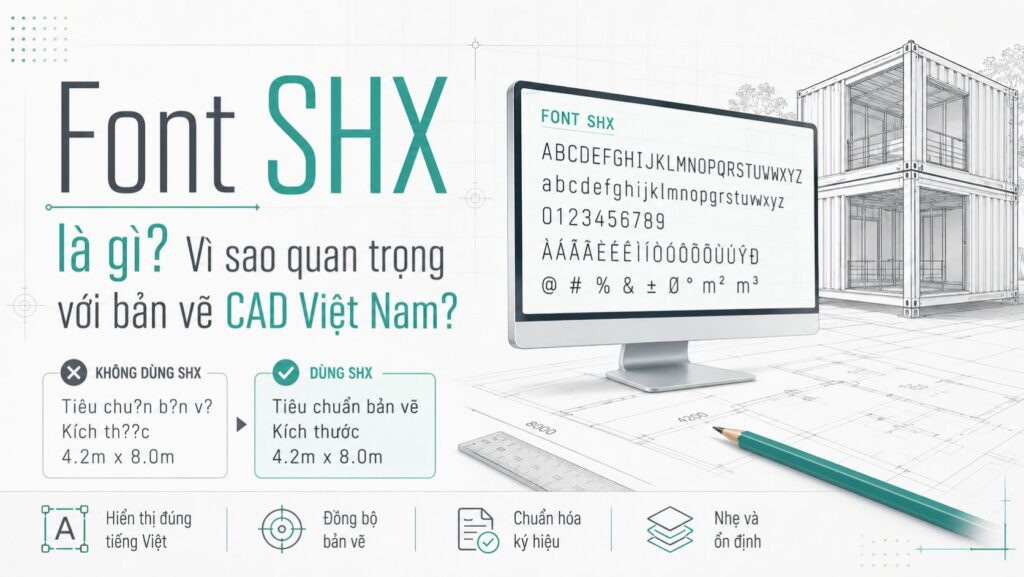
15+ loại font SHX phổ biến trong AutoCAD
Trong AutoCAD, font SHX được chia thành nhiều nhóm phục vụ từng mục đích khác nhau, từ font kỹ thuật tiêu chuẩn đến font tiếng Việt và Big Font cho các bộ ký tự lớn.
Font SHX chuẩn AutoCAD
Đây là nhóm font được sử dụng phổ biến trong các bản vẽ kỹ thuật nhờ khả năng hiển thị nhanh, nhẹ và tương thích tốt với AutoCAD. Một số nhóm font SHX gồm có:
Trong đó, simplex.shx được dùng làm font thay thế mặc định qua thiết lập FONTALT, còn nhóm Roman và ISO phù hợp với nhiều tiêu chuẩn trình bày bản vẽ kỹ thuật.
Font SHX tiếng Việt phổ biến
Các bộ font SHX tiếng Việt xuất hiện trong bản vẽ kiến trúc, kết cấu và MEP tại Việt Nam. Việc cài đủ các font này giúp hạn chế lỗi mất dấu, sai ký tự hoặc chữ bị thay thế khi mở file DWG.
Trong đó, VNSIMPLE SHX, VNSIMLI SHX và font 3T Unicode SHX là những tên thường gặp khi người dùng cần bổ sung font cho bản vẽ CAD tiếng Việt.
Big Font SHX
Big Font được thiết kế cho các ngôn ngữ có số lượng ký tự lớn và chỉ sử dụng với định dạng SHX. Người dùng có thể bật Use Big Font trong Text Style rồi chọn file phù hợp.
Với lệnh STYLE, font được khai báo theo cú pháp fontname, bigfontname. Việc chọn đúng Big Font giúp bản vẽ hiển thị chính xác các ký tự đặc biệt và hạn chế lỗi font khi trao đổi file giữa nhiều máy.
Font SHX được ứng dụng như thế nào?
Font SHX được sử dụng chủ yếu trong các bản vẽ kỹ thuật AutoCAD nhờ ưu điểm nhẹ, hiển thị nhanh và dễ kiểm soát khi in ấn. Đặc biệt, định dạng này phù hợp với những hồ sơ có nhiều text, ký hiệu hoặc yêu cầu đồng bộ font giữa các máy tính.
Một số ứng dụng phổ biến của font SHX gồm:
- Bản vẽ kiến trúc: ghi chú mặt bằng, mặt đứng, mặt cắt, kích thước và ký hiệu kỹ thuật.
- Bản vẽ kết cấu: Thể hiện tên cấu kiện, cao độ, ký hiệu thép và chú thích thi công.
- Bản vẽ MEP: Dùng cho hệ thống điện, cấp thoát nước, điều hòa, phòng cháy chữa cháy.
- Bản vẽ cơ khí: Ghi kích thước, dung sai, ký hiệu hình học và thông số kỹ thuật.
- Hồ sơ hạ tầng: Áp dụng trong bản vẽ giao thông, san nền, cấp thoát nước và quy hoạch.
- Bản vẽ CAD tiếng Việt: Các font như vnsimple.shx, vnsimli.shx hay 3T Unicode SHX giúp hiển thị nội dung tiếng Việt đúng hơn khi trao đổi file giữa nhiều máy.